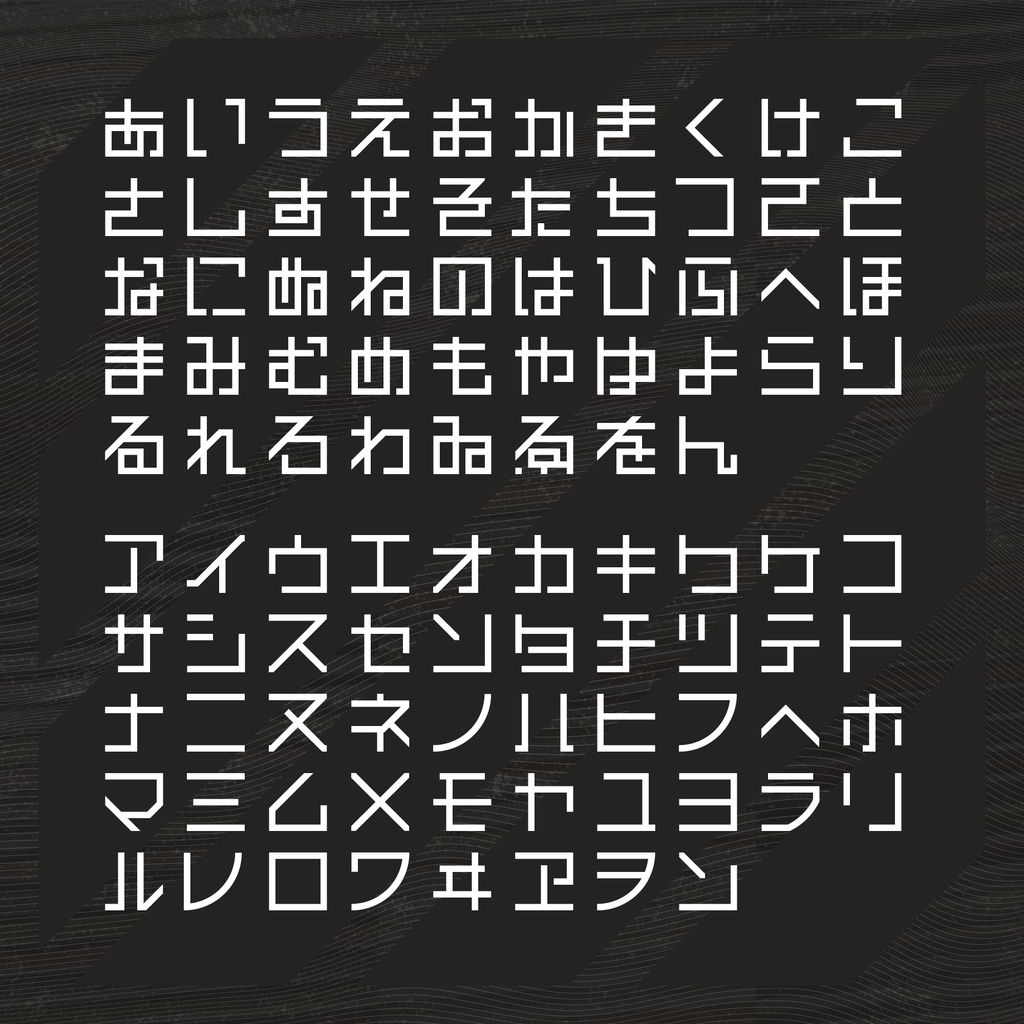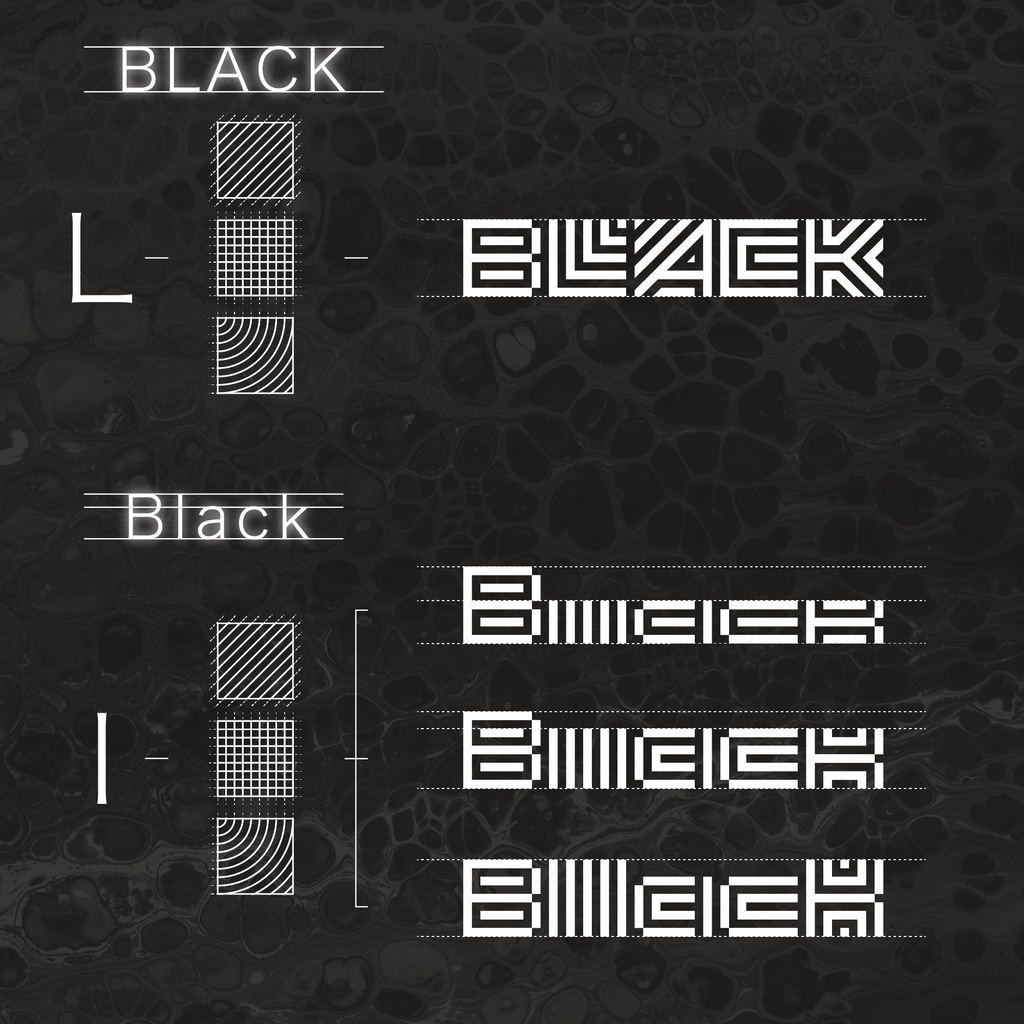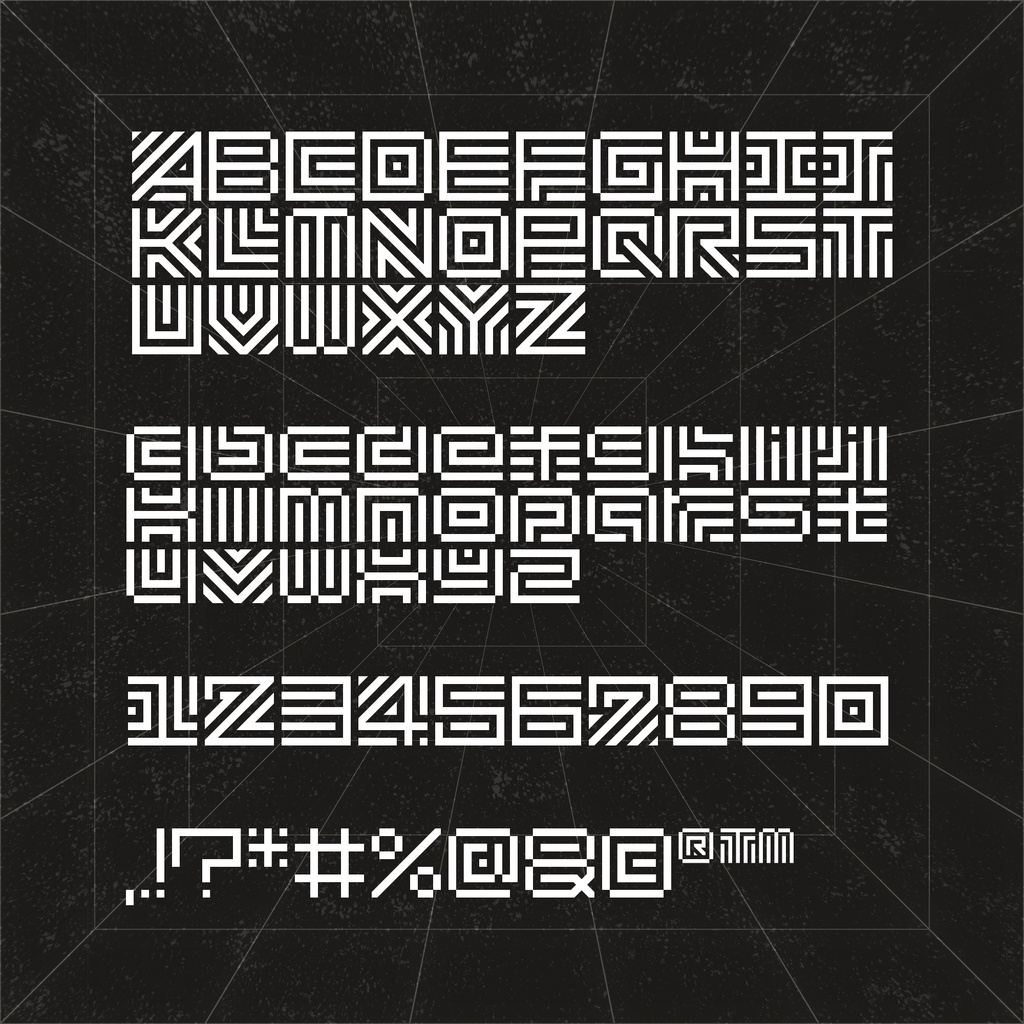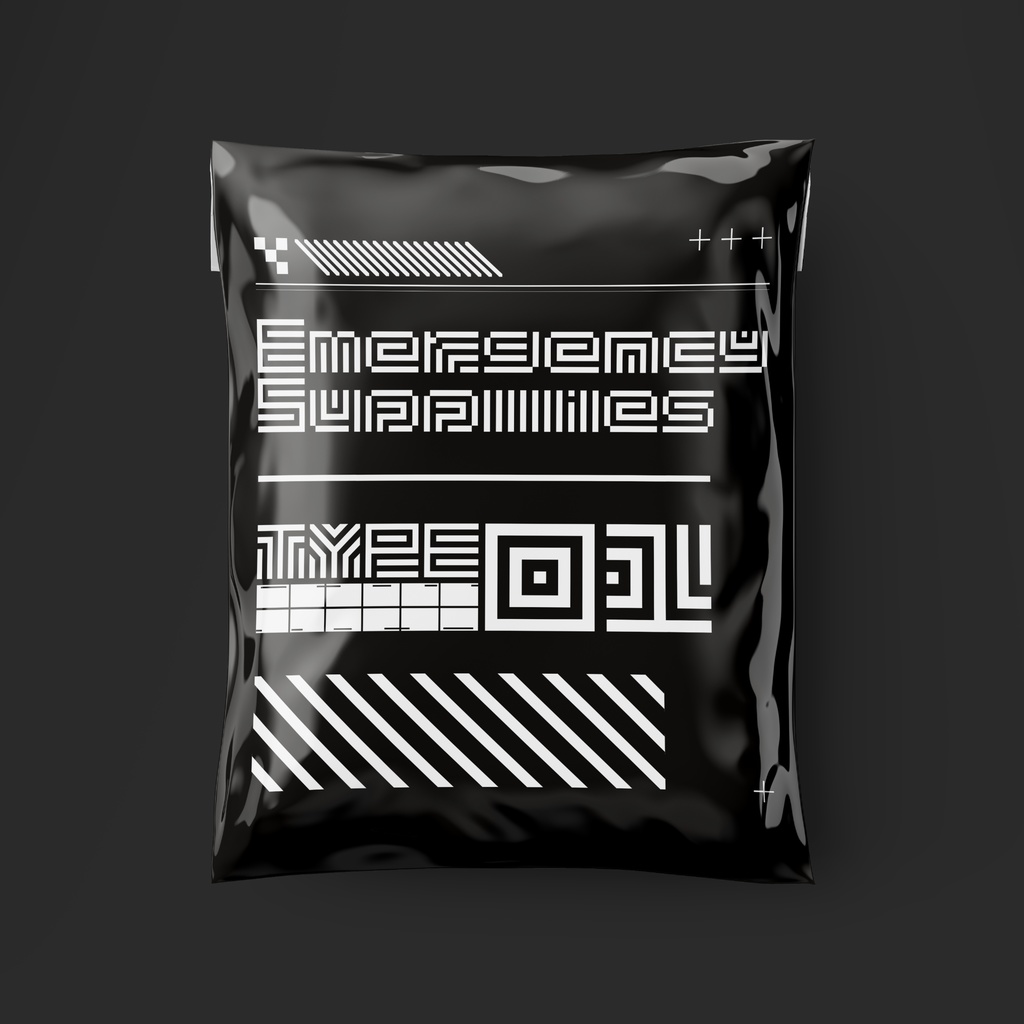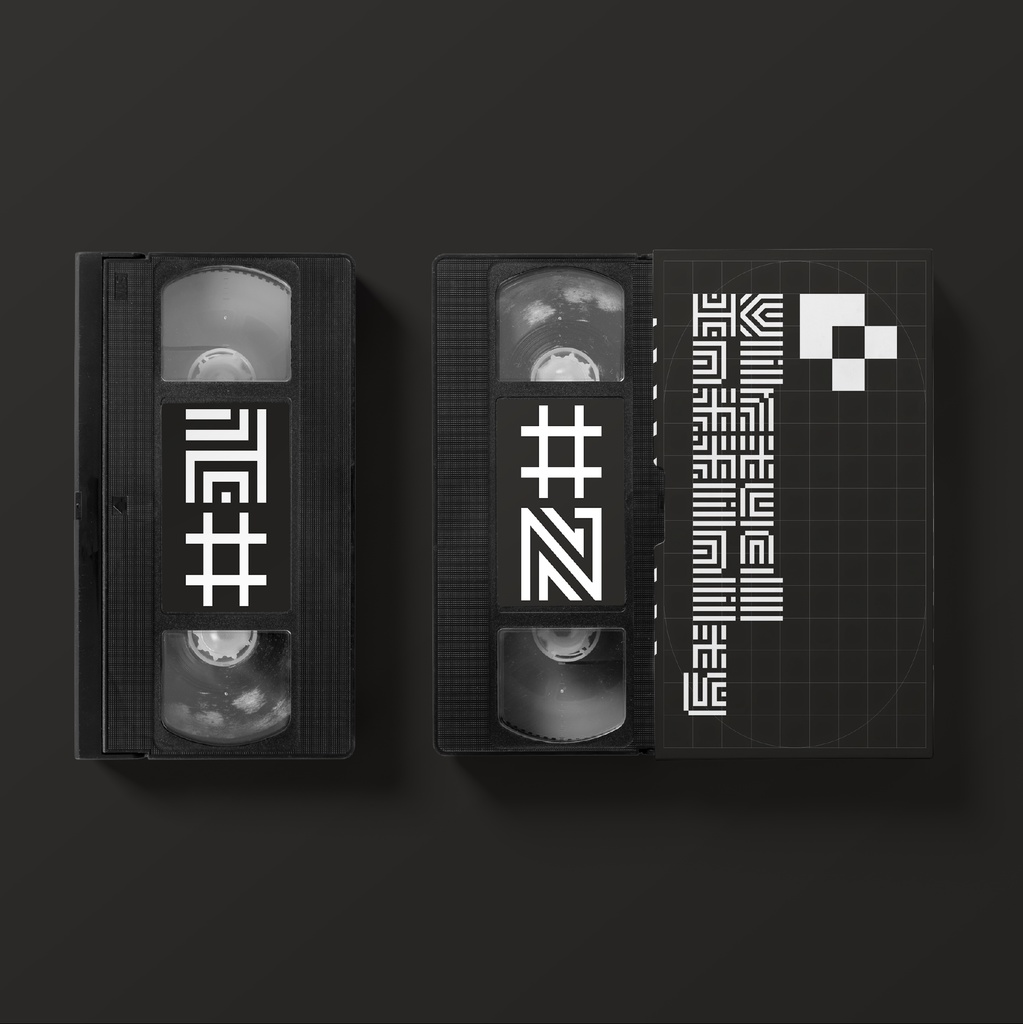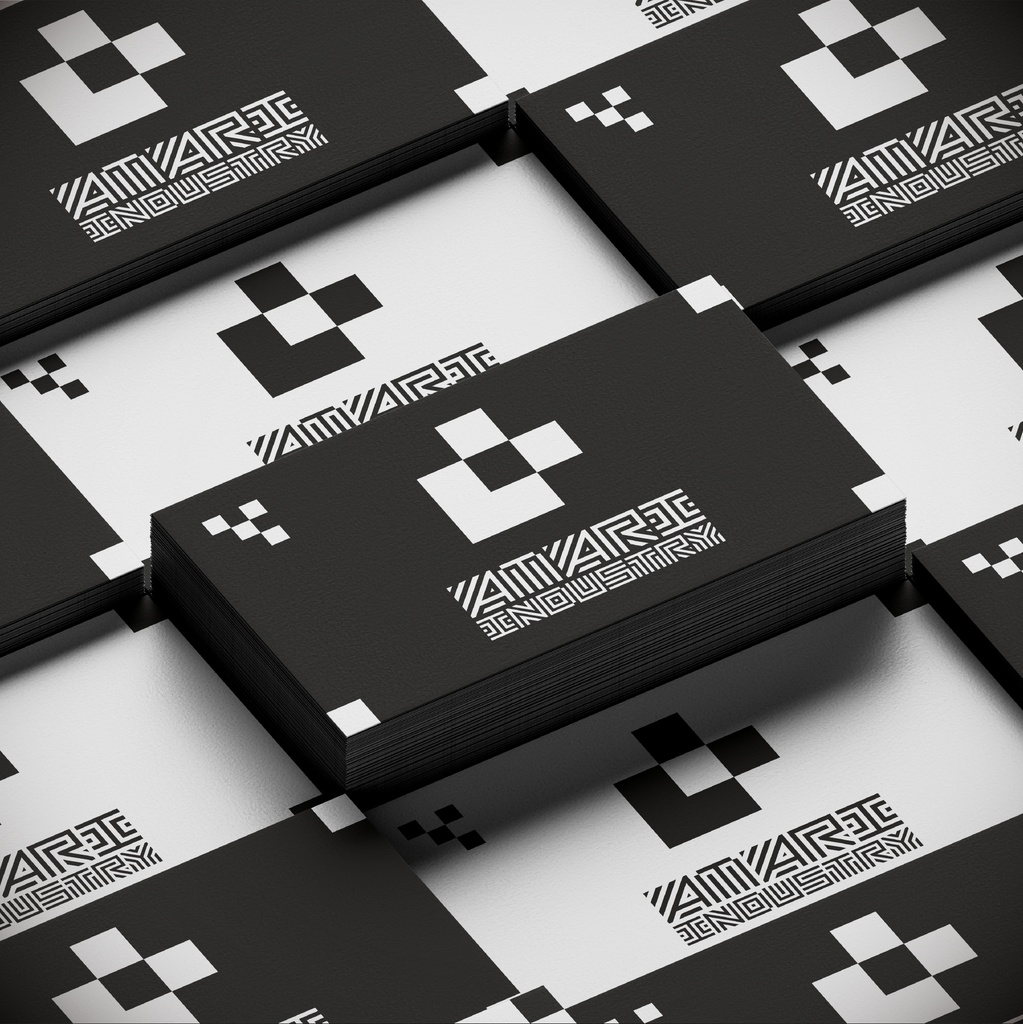
「旧バージョン」【フリーフォント】騒音警示 Nosie Warning
騒音警示|Nosie Warning 「旧バージョン」 📢📢📢特記事項📢📢📢 新バージョンが完成しましたので、このフォントをご利用の際は最新版をご利用ください。 ▼新バージョン https://amaridesign.booth.pm/items/3503863 📢デザイン説明 騒音警示は、主な設計仕様として9×9グリッドと対応サイズの弧と斜線の作るのフリーフォントです。 これはわれら作成する最初のフォントです。 このフォントは、今年の「騒音」の作字を拡張した内容です。 長さと幅、そして字の占有面積と空間の視覚的平衡調整をつり合わせます。 これにより、このフォントにテクノロジーと超現実的な視覚効果を感じできる。 このフォントは、未来風な科学的な感覚のデザインに使いで非常に適しています。 他の未來風と科学技術の感じを持ったフォントと組み合わせて使用することも適しています。 Twitterで@ orange634ntyが開催した#作字#AdventCalendar2021イベントに参加したので、このプロジェクトを作りました。 📢利用規約 このフォントは無料でダウンロードできる。 個人、商用どちらでも利用可能です。 もしこの素材が使用されたら、https://twitter.com/amari_designに教えていただければ嬉しいです! 当素材をご利用頂いている配信や画像等を実績として公開させて頂くことがございます。ご了承下さい。 フォントのインストール等の技術的なサポートはいたしません。使用して発生したと思われる如何なる問題についても、作者は責任を負わないものとします。 著作権を放棄することはありません。 商標を登録したり、作者であると主張したり、データ自体を販売または再販したりすることは禁じられています。 このコンテンツの最終的な解釈権は作者に帰属します。 内容補充とバージョン更新は製作続けるです。使用する際は最新バージョンにご注意ください。 📢収録內容 英語の文字、ギリシア文字、日本語の仮名、および一般的な句読点を含む475文字が含まれています(一部のフォントには複数の選択肢があります)。 ーーーーーーーーーーーー Twitter:https://twitter.com/amari_design Behance:https://www.behance.net/9f45706b ーーーーーーーーーーーー